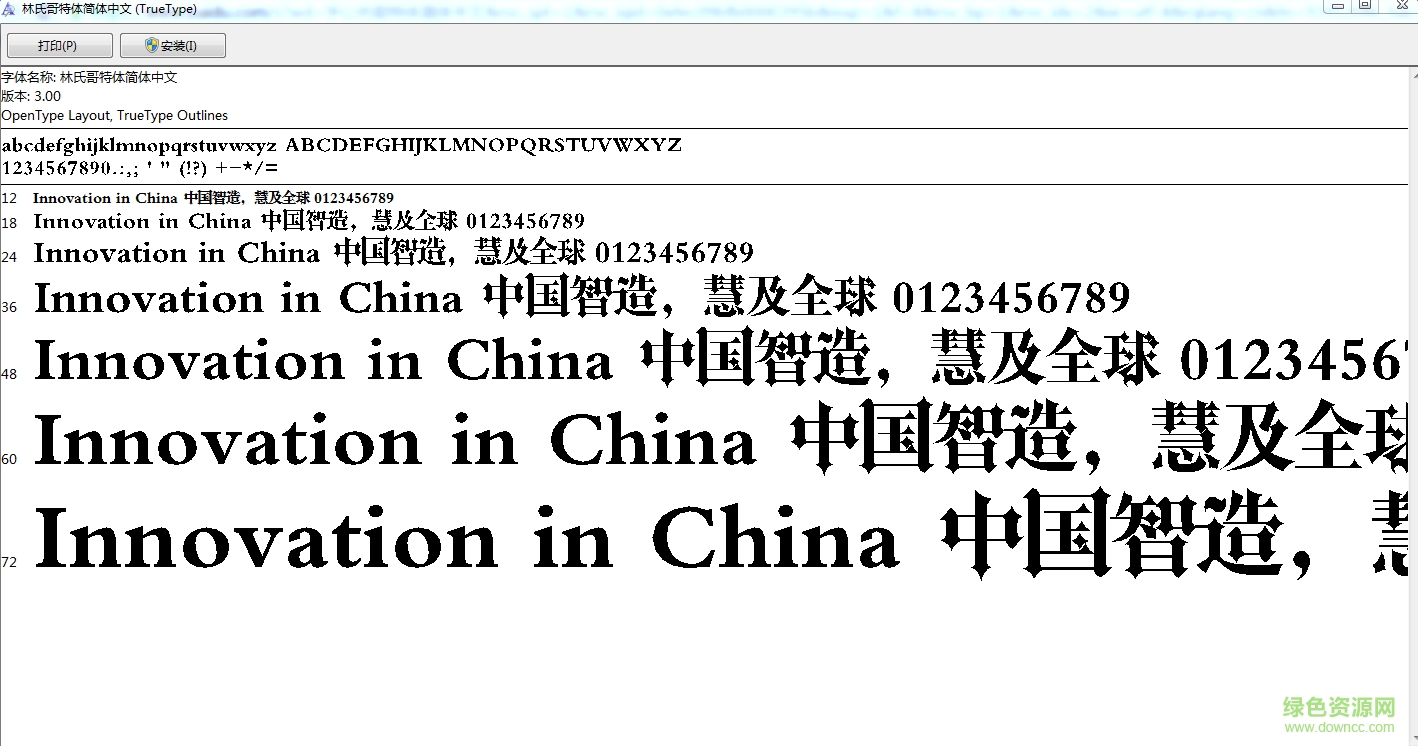
字心坊李林哥特體簡體中文字體是一款林氏哥特體完整版字體,該字體具有獨特的哥特式風格和樣式,時尚好看,辨識度高,喜歡的朋友歡迎在綠色資源網(wǎng)下載!
是一款用于游戲設計方面的字體,該字體以是哥特式字體為原型說創(chuàng)作出的一款字體,識別性強,字體獨特,本作品適用于游戲設計字體、藝術設計字體、影視設計字體。